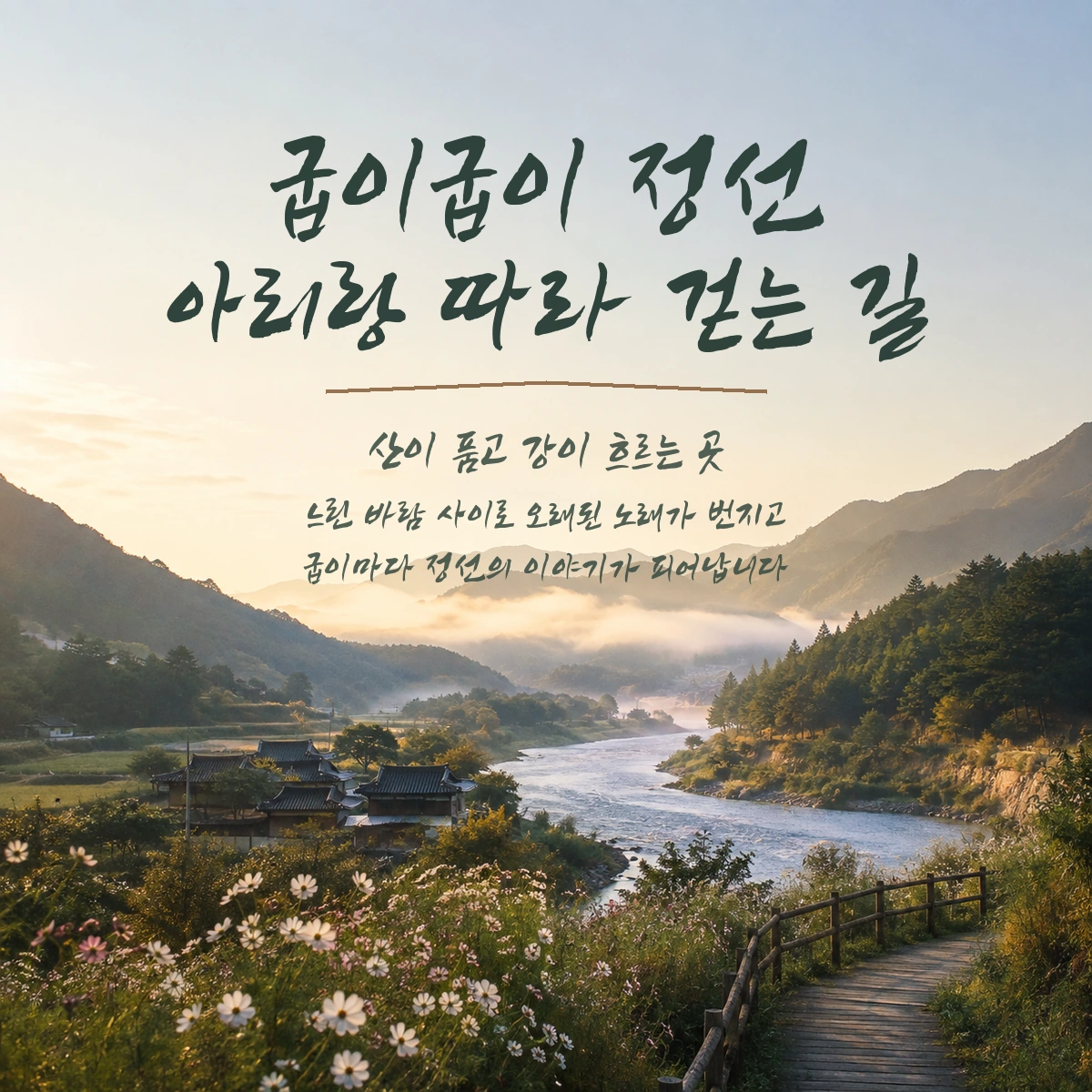
정선아리랑체 — 정선군에서 배포하는 무료 폰트입니다. 정선의 대표 문화유산인 아리랑에서 이름을 얻은, 굽이치는 획이 정취를 담아내는 캘리그라피 서체
정선군이 2017년에 공개한 전용서체입니다. 정선동강체와 함께 나왔고, 강원도 내 지자체 가운데 처음으로 만든 전용서체로 알려져 있습니다.
이름은 정선의 대표 문화유산인 아리랑에서 왔습니다. 여기서 한 가지 바로잡을 것이 있습니다. 정선아리랑은 흔히 국가무형문화재로 알려져 있지만 실제로는 **강원도 무형유산 제1호**로, 1971년에 지정됐습니다. 정선 산간마을 주민들의 생활 감정이 담긴 민요로 아라리라고도 불립니다.
군이 밝힌 조형 설명은 짧습니다. 아리랑의 역사와 자존심을 담고 있는 캘리그래피 서체이며 힘이 느껴지는 획의 표현이 특징이라는 것입니다. 파일에서 재어 보면 받침이 붙을 때 글자 높이가 달라지는 탈네모틀이고 획이 그리 굵지 않습니다. 민요 자체는 서글픔으로 이야기되지만 서체는 힘 쪽을 택했으니, 두 인상을 그대로 겹쳐 생각하지는 마세요.